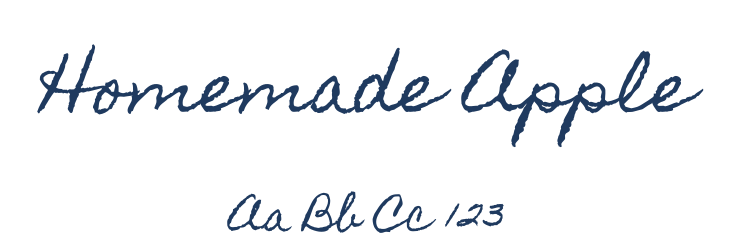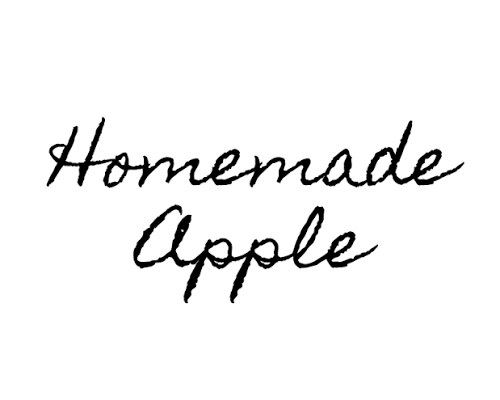
Homemade Apple font Việt hóa là bộ phông chữ thuộc dòng Cursive Script mộc mạc do Font Diner sáng tạo, lấy cảm hứng từ nét chữ viết tay nắn nót của người nội trợ trên những tấm thiệp ghi chép công thức làm bánh gia đình thuở trước. Với các đường nét nghiêng ngả tự nhiên, độ dày nét thanh mảnh và vẻ ngoài đầy ắp sự yêu thương, Homemade Apple font là chất liệu trực quan tuyệt vời để các kiến trúc sư, nhà thiết kế mang lại sự ấm áp cho các bản vẽ phối cảnh tiệm bánh ngọt container, góc bếp homestay đồng quê hay các bảng menu phấn đen thủ công.
Nét nghiêng bình dị và cảm xúc ấm cúng của Homemade Apple font Việt hóa
Điểm cuốn hút của Homemade Apple font Việt hóa nằm ở sự không hoàn hảo có chủ đích, mô phỏng sinh động chuyển động nhịp nhàng của ngòi bút bi trên giấy nhám. Từng chữ cái sở hữu các vòng lặp mềm mại và độ nghiêng tự do, mang lại cảm giác thân quen như đang đọc một dòng ghi chú nhắn gửi của người thân trên cánh cửa tủ lạnh.
Sự ổn định về mặt cảm xúc của dòng font này giúp khơi gợi cảm giác an yên, lòng mến khách và sự trân trọng những giá trị gia đình bình dị. Khi kết hợp cùng các vật liệu kiến trúc mộc mạc như tường gạch thẻ nung cổ, vách gỗ thông tự nhiên, rèm vải caro hay bàn đá mộc trong các căn nhà lắp ghép nghỉ dưỡng, Homemade Apple tạo nên sự hòa quyện thẩm mỹ êm dịu.
| Phân loại phong cách | Casual Script / Handwritten / Vintage Recipe Style |
| Mục đích phù hợp | Menu tiệm bánh, biển tên homestay đồng quê, tranh trích dẫn |
Tư vấn từ chuyên viên: Homemade Apple sở hữu nét chữ viết tay nhẹ nhàng và độ thanh thoát cao. Để bản thiết kế đạt hiệu quả thẩm mỹ tốt, bạn nên sử dụng phông chữ này cho các tiêu đề phụ, câu trích dẫn hoặc bảng thực đơn ngắn.
03 Ứng dụng phông chữ Homemade Apple vào không gian công trình
Nhờ vẻ ngoài bình dị và tính gợi cảm xúc gia đình ấm cúng, bộ phông chữ này mang lại giá trị thực tế lớn trong khâu trang trí các không gian dịch vụ hoài cổ:
- Bảng thực đơn và Biển tên món cho Tiệm bánh Container: Những nét chữ viết tay nắn nót của Homemade Apple rất ăn ý khi in ấn trên nền bảng phấn đen hoặc dán decal trên kính quầy pha chế, mang lại diện mạo mộc mạc và cảm giác ngon miệng cho thực khách.
- Hệ thống biển tên phòng và Bảng nội quy Homestay Đồng quê: Phông chữ này khi sơn thủ công trên các thanh gỗ thông hoặc bảng gốm nung men sẽ giúp các căn phòng trong khu nhà lắp ghép toát lên chất thơ, mang lại trải nghiệm nghỉ dưỡng thư thái cho du khách.
- Trang trí không gian bếp ăn chung và Góc bàn ăn gia đình: Bạn có thể dùng phông chữ này để làm tranh chữ trích dẫn phong cách sống, nhãn dán lọ gia vị hoặc công thức nấu ăn treo tường, tạo bầu không khí ấm cúng cho không gian sinh hoạt.
03 Lưu ý bố cục font Homemade Apple luôn tự nhiên và dễ đọc
Để khai thác hiệu quả vẻ đẹp của dòng font viết tay đời thường này mà không gây cảm giác lộn xộn cho trang giấy, người thiết kế nên lưu tâm một số kinh nghiệm sau:
- Tránh viết hoa toàn bộ ký tự: Các chữ cái in hoa của Homemade Apple có cấu trúc nghiêng ngả tự do. Việc viết hoa liên tiếp nhiều chữ cái sẽ làm các nét móc đè chồng lên nhau, gây mất trật tự thị giác và khiến câu văn trở nên khó đọc.
- Kiểm soát khoảng cách dòng: Do các nét vươn lên trên và rủ xuống dưới của ký tự khá dài, bạn nên thiết lập khoảng cách dòng thoáng đãng (khoảng 1.5 – 1.6 lần cỡ chữ) để các dòng chữ không bị va chạm nhau.
- Lựa chọn gam màu ấm áp dịu nhẹ: Homemade Apple phát huy hiệu quả thị giác cao khi phối cùng màu nâu cà phê, xanh rêu nhạt, trắng kem hoặc cam đất trên nền vật liệu gỗ hoặc giấy kraft, làm nổi bật đường nét chân phương của bộ chữ.
2. Phông chữ này có hỗ trợ đầy đủ các ký tự số không?